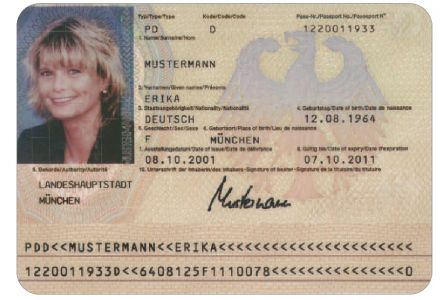
Sehr schöne Beispiele,
eine Mischung von Vorschlag 4 und 5, und dann ein großes ß mit Unterlänge und Erinnerung an das kurze (runde s) würde mir persönlich am besten gefallen. Damit wäre eine sehr gute Unterscheidung zu dem Zeichen B gegeben und dieses missverständliche z wäre nicht erhalten, wie beispielsweise in Vorschlag 2 und 6.
Hoffentlich tut sich trotzdem vielleicht an anderer Stelle irgendwo etwas, um die Peinlichkeit des seit 60 Jahren fehlenden Großbuchstaben ß zu beheben.
In der DDR der 50er und 60er waren die Buchstabenkombinationen "SS" und "SA" unerwünscht. Das führte sogar zu einer Veränderung der Schreibweise mancher Namen. Ich denke, daß das der Grund für die gezeigte Duden-Bezeichnung war.
Weiß jemand was für eine Schrift im Personalausweis benutzt wird?
Hier wird doch ein versales ß für Eigennamen dringend benötigt!
Wie wird hier verfahren? Hat jemand der Bundesdruckerei schon ein versales ß gebastelt, bzw. eine Schrift verkauft?
Weiß jemand was für eine Schrift im Personalausweis benutzt wird?
Das ist die OCRB von Adrian Frutiger.
Meines wissens wird ß zu SS --> kann zu netten Verwechslungen etc. kommen...
Habe auf die selbe Frage von Thomas bereits im typeFORUM.de geantwortet:
In meinem Namen (Preuß) wird er typographisch völlig falsch mit PREUß eingetragen, wie bei jedem anderen auch, der diesen Buchstaben im Namen trägt. Also keine sonst vom DUDEN vorgeschlagene Umschreibung mit SS (PREUSS), da dieses in Amtsdeutsch schlicht und ergreifend falsch ist. Ich heiße nun mal Preuß und nicht Preuss; wie jemand eben Müller und nicht Mueller heißt…
Meines wissens wird ß zu SS
Das glaube ich kaum! Ich gehe jede Wette ein, dass sie »STRAUß« schreiben.
Kann es sein, dass es in Österreich anders ist? Ich will mich nämlich daran erinnern dass ich das mal gesehen habe und mir gedacht habe "das ist doch Wahnsinn".
Ich werde mich mal auf die Suche begeben, nur fällt mir im Moment niemand in meinem Bekanntenkreis ein der ein ß im Namen trägt.
Ich schrieb doch: mein Name wird mit PREUß geschrieben. Zum 'Beweis' nachfolgendes Bild:
Ich muß aber sagen, daß das ß so schlecht nicht ist - auch wenn es sich um ein Kleinbuchstabe handelt. Man sieht es aber kaum, denn die Schutzhülle hat ein Rillenmuster, was einen vernünftigen Scan fast unmöglich macht.
Die Bundesdruckerei wäre wohl ein dankbarer Abnehmer einer Schrift mit Versal-ß.
Das ist die OCRB von Adrian Frutiger.
Kommt nicht ganz ran, man sieht es deutlich beim S und beim G.
Dagegen ist die OCR-B wohl die Schrift, die im unteren Drittel des Personalausweises benutzt wird (ist bei Ingo Preuß nicht abgebildet, dafür weiter oben beim Personalausweismuster von Erika Mustermann).
vom Rat für deutsche Rechtschreibung bekam ich heute nach einem
dreiviertel Jahr eine Antwort auf meine Anfrage zum Bedarf eines
Versal-ß. Zur Info gebe ich es hier wieder.
Er schreibt:
„Der Bedarf nach einem Großbuchstaben für "ß" wurde früh angemeldet,
beispielhaft darf ich Ihnen aus der neunten Auflage des Rechtschreibdudens
aus dem Jahre 1925 zitieren (Vorbemerkungen, XII): "Für ß wird in großer
Schrift SZ angewandt, z.B. MASZE (Maße) - aber MASSE (Masse) -, STRASZE,
PREUSZEN, MEISZNER, VOSZ. Die Verwendung zweier Buchstaben für einen Laut
ist nur ein Notbehelf, der aufhören muss, sobald ein geeigneter
Druckbuchstabe für das große ß geschaffen ist."
Es ist also eine Frage, die schon seit Jahrzehnten unbeantwortet ist und es
wohl auf geraume Zeit auch bleiben wird. Der Grund hierfür liegt darin,
dass es dem Rat für deutsche Rechtschreibung nicht zusteht, Schriftzeichen
zu erfinden. Seine Aufgabe ist es, die Schreibung zu beobachten und darauf
zu achten, dass Regeln und Schreibgebrauch sich im Einklang befinden. Es
bedarf also einer Initiative aus der Schreibgemeinschaft (z.B. vonseiten
der Typografen), um hier auf der Basis eines gesellschaftlichen Konsenses
Abhilfe zu schaffen.
Zur Schreibung von "ß" in behördlichen Dokumenten: Der Eindeutigkeit halber
ist man hier dazu übergangen, "ß" auch bei der Großbuchstabenschreibung
beizubehalten, also z.B. "GROßMANN" für "Großmann" zu schreiben. Diese
Verwendung begegnet auch immer öfter in der Werbung.
Nebenbei noch - da Sie es nicht in Erwägung ziehen, nehme ich schweigende
Zustimmung an: "ß" durch "SZ" zu ersetzen, verbietet sich wegen der
polnischen Namen, die oft diese Kombination aufweisen.“
Ende des Zitats
Das heißt also, dass es doch eine gewisse (offizielle) Legitimation gibt, in Versalschreibweise das normale »ß« zu benutzen.
Die Schaffung eines Versal-ß liegt nun also an uns. Also, ran an die Editoren … :D
Okay, dann müssen wir es nur noch im Alltagsgebrauch durchsetzen …
Bedarf ist ja – wie es aussieht – in der Werbung, in Unternehmen und bei Behörden vorhanden. Dieses Verkaufsargument lässt sich bestimmt zum Vorteil nutzen (im Gegensatz zu Fonts, die kein Versal-ß besitzen).
Und jetzt noch eine Vorankündigung: Ende März wird in der Reihe SIGNA das neue Heft mit dem Thema "Das große Eszett" erscheinen; darin ausführliche Beiträge zu sprachlichen, schriftgeschichtlichen und gestalterischen Aspekten. Einige Ausgrabungen (Aktivitäten um das versale ß *vor* 1900) werden dabei für Überraschung sorgen.